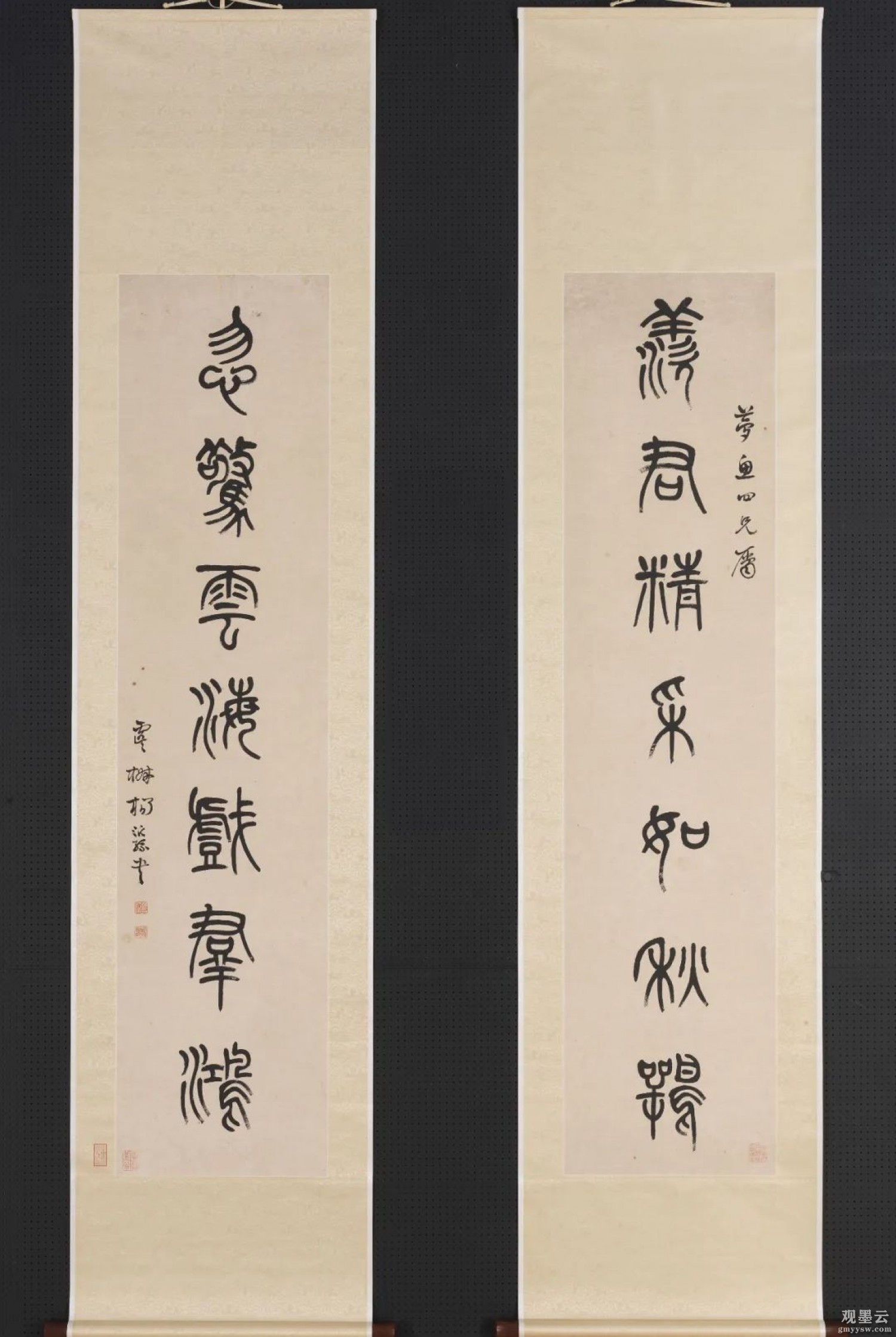
释文:羡君精采如秋鶚,忽惊云海戏羣鸿。梦鱼四兄属虞椒杨沂孙书。
杨沂孙字泳春,号子舆,晚署豪叟,中国江苏常熟城区人。少从李兆洛学,精於《管子》、《庄子》。道光二十叁年(1843年)举人,官至安徽凤阳知府。杨以篆书着称於世,尤爱“篆籀之学”,初学怀寧邓石如,后吸收金文、石鼓文、汉碑篆书,遂自成一格,直追唐人李阳冰;马宗霍《霋岳楼笔谈》评其篆书:「濠叟篆书,功力甚勤,规矩并备,所乏者韵耳」。《七言联》為晚年作品。著作有《管子今编》、《庄子正读》、《文字说解问偽》、《在昔篇》、《观濠居士集》等。